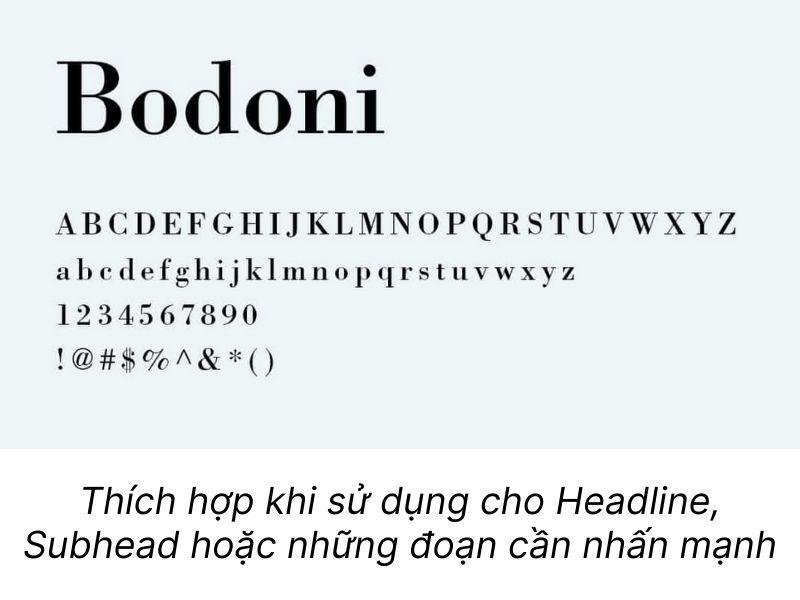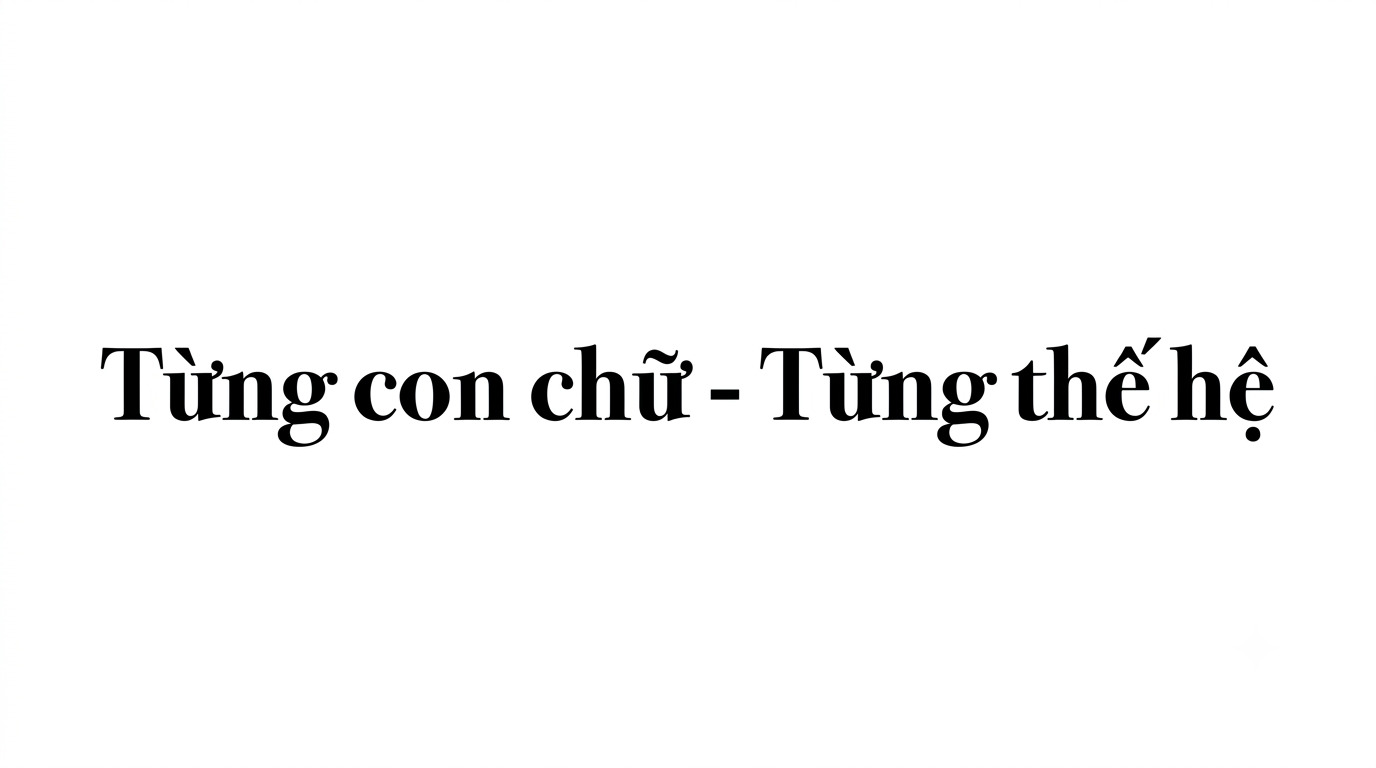
Nhiều designer khi sử dụng font Bodoni thường gặp lỗi thiếu dấu tiếng Việt hoặc các nét chữ thanh mảnh bị đứt gãy khi thu nhỏ, in ấn trên hộp quà trang sức và bao bì cao cấp. Những vấn đề này làm giảm sự tinh tế của thiết kế, khiến hình ảnh thương hiệu chưa thể hiện được phong cách sang trọng vốn có.
Font Bodoni là gì?
Font Bodoni là một trong những phông chữ kinh điển nhất thế giới, thuộc dòng Modern Serif (chữ có chân hiện đại), được thiết kế bởi nghệ nhân Giambattista Bodoni vào cuối thế kỷ 18. Đặc trưng nổi bật nhất của Bodoni là sự tương phản cực hạn giữa các nét đậm vững chãi và các nét thanh mỏng manh như sợi tơ. Cấu trúc chữ có trục thẳng đứng cùng các đường chân (serif) nằm ngang phẳng, tạo nên một vẻ đẹp đầy quyền quý, tinh tế và đậm chất thời thượng.
Trong ngành đồ họa quốc tế, Bodoni thường được mệnh danh là “ông hoàng của phông chữ thời trang”, xuất hiện xuyên suốt trên các bìa tạp chí danh tiếng như Vogue hay Harper’s Bazaar. Tuy nhiên, cấu trúc hình học khắt khe của nó đòi hỏi kỹ thuật xử lý dấu tiếng Việt rất tỉ mỉ để không làm mất đi tính đối xứng. Bản font Bodoni Việt hóa full tại In Viva đã được căn chỉnh kerning, đảm bảo các ký tự có dấu hiển thị mượt mà, giúp bản thiết kế của bạn luôn sang trọng trên mọi chất liệu từ giấy Ivory đến gốm sứ cao cấp.
Lưu ý: Với cấu trúc nét thanh nét đậm đặc thù, khi in ấn font Bodoni trên bề mặt gốm sứ hay kim loại, designer nên tăng nhẹ độ dày Stroke (khoảng 0.1pt) để đảm bảo hình in không bị mất chi tiết sau khi gia công nhiệt.
5 ứng dụng của font Bodoni Việt hóa trong thiết kế và in ấn
Với phong cách thanh lịch và giàu tính nghệ thuật, Bodoni giúp tạo điểm nhấn cho các sản phẩm thuộc phân khúc cao cấp khi kết hợp cùng công nghệ in ấn và gia công tại Xưởng In Viva:
- Thiết kế bao bì hộp quà yến sào và trang sức: Bodoni phù hợp để thể hiện tên thương hiệu trên nắp hộp cứng cao cấp. Sự kết hợp giữa nét chữ thanh mảnh và kỹ thuật ép kim nhũ vàng, bạc giúp sản phẩm thể hiện phong cách tinh tế, phù hợp với các dòng quà biếu sang trọng.
- Sản xuất túi giấy thời trang và mỹ phẩm: Font Bodoni trên túi giấy Ivory hoặc giấy mỹ thuật giúp các thương hiệu thời trang, mỹ phẩm tạo dấu ấn riêng nhờ kiểu chữ Serif cổ điển, phù hợp với phong cách tối giản và thanh lịch.
- In ấn quà tặng gốm sứ tri ân đối tác: Logo sử dụng font Bodoni khi in nung trên bộ ấm chén sứ tạo điểm nhấn nhẹ nhàng, phù hợp với các sản phẩm quà tặng doanh nghiệp dành cho khách hàng và đối tác.
- Thiết kế thiệp mời và voucher sự kiện: Bodoni thường được sử dụng cho tiêu đề hoặc thông điệp chính trên thiệp mời, voucher cao cấp. Khi kết hợp cùng kỹ thuật dập nổi hoặc ép kim, kiểu chữ giúp ấn phẩm trở nên nổi bật hơn.
- Khắc laser bình giữ nhiệt và sổ tay bìa da: Logo dùng font Bodoni khi khắc trên kim loại, da hoặc gỗ giúp tạo cảm giác tinh tế, phù hợp với các dòng quà tặng doanh nhân và sản phẩm cá nhân hóa.
5 lưu ý khi sử dụng font chữ Bodoni Việt hóa
Để thiết kế sử dụng Bodoni hiển thị rõ nét và phù hợp với từng phương pháp sản xuất, designer nên chú ý các yếu tố sau:
- Kiểm soát độ dày nét thanh (Hairlines): Bodoni có sự tương phản lớn giữa nét thanh và nét đậm. Khi in trên giấy Kraft hoặc các chất liệu có độ hút mực cao, nên lựa chọn kích thước chữ phù hợp hoặc điều chỉnh độ dày nét để hạn chế tình trạng mất chi tiết.
- Tối ưu đường Path cho gia công bế nổi: Khi sử dụng Bodoni để dập nổi logo trên hộp quà cao cấp, file vector cần được kiểm tra và xử lý các điểm neo nhỏ. Việc tối ưu đường Path giúp các chi tiết chân chữ được thể hiện rõ hơn trên giấy mỹ thuật, Ivory hoặc carton lạnh.
- Hạn chế sử dụng cho nội dung dài: Bodoni phù hợp với tiêu đề, logo, tên thương hiệu hoặc slogan ngắn. Với các đoạn văn bản dài, cỡ chữ nhỏ có thể làm giảm khả năng đọc do đặc điểm nét chữ tương phản cao.
- Lựa chọn kỹ thuật gia công phù hợp: Font Bodoni thường phù hợp với các kỹ thuật như ép kim, phủ UV định hình hoặc dập nổi để làm nổi bật các đường nét đặc trưng. Việc lựa chọn phương pháp gia công nên dựa trên chất liệu và kích thước sản phẩm.